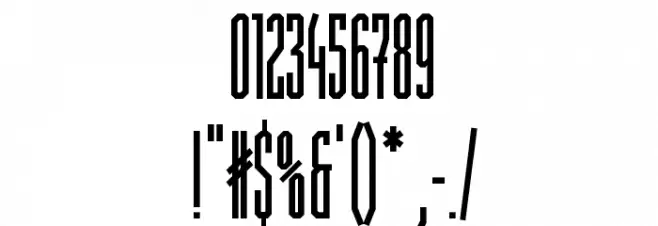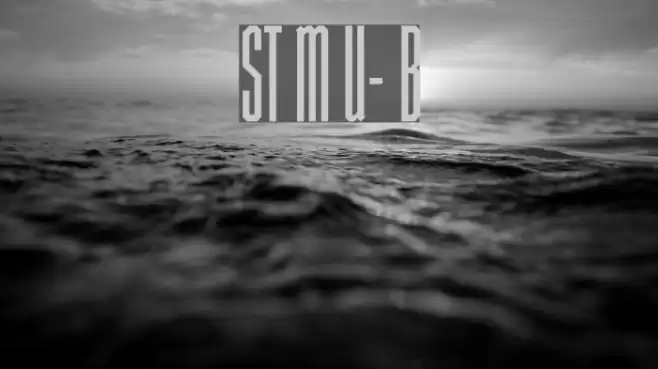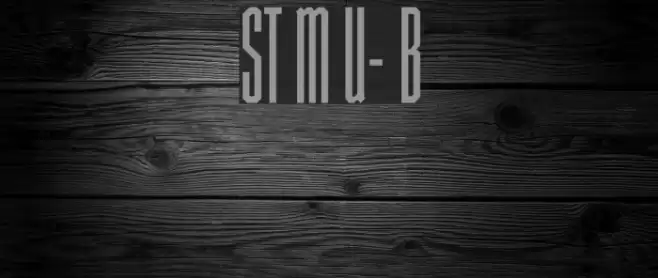
ST Moviehead Ultra-condensed Bold Font
| Vorgeschlagene Projekte | Ideal for movie posters, magazine covers, branding, and advertising where a bold statement is needed. |